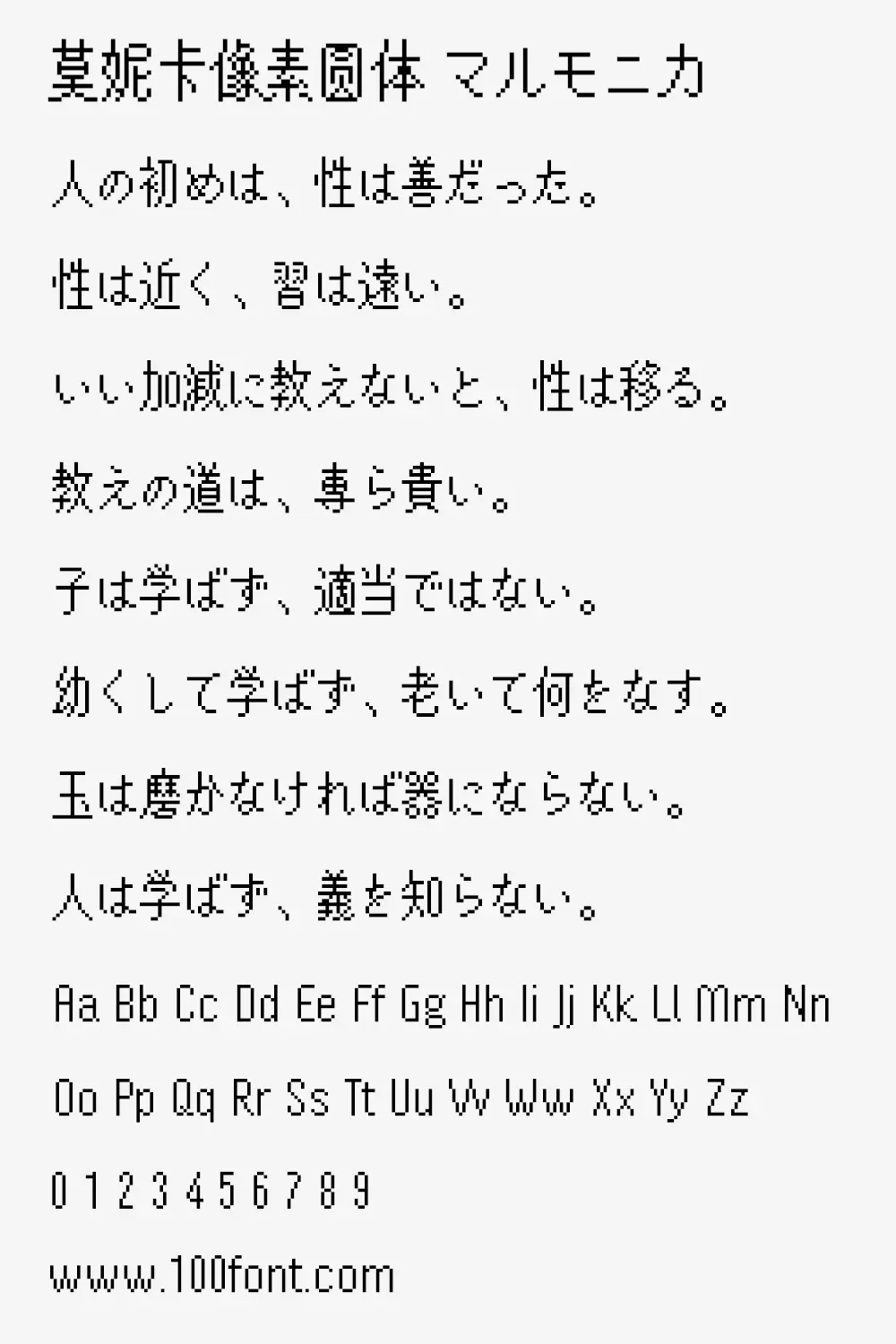
■追求像素形成的曲線美。
是兼具“柔軟”和“嚴肅”的像素字體。
JIS第1水準漢字2965字,第2水準漢字3390字完全收錄!
打印標準字體1022字也對應。
■美麗的歐文,充實的多語言對應。
支持使用拉丁文字、西里爾文字的多種語言。
通過獨特的字間調節,即使在沒有字距調整功能的遊戲開發環境中也能實現自然美麗的歐文表示。
■ ピクセルが形作る曲線美を追求。
「柔らかさ」と「シリアスさ」を併せ持つピクセルフォントです。
JIS第1水準漢字2965字、第2水準漢字3390字を完全収録!
印刷標準字體1022字にも対応しています。
■ 美しい歐文、充実の多言語対応。
ラテン文字、キリル文字を用いる多數の言語に対応。
獨自の字間調節により、カーニング機能のないゲーム開発環境でも自然で美しい歐文表示を実現します。